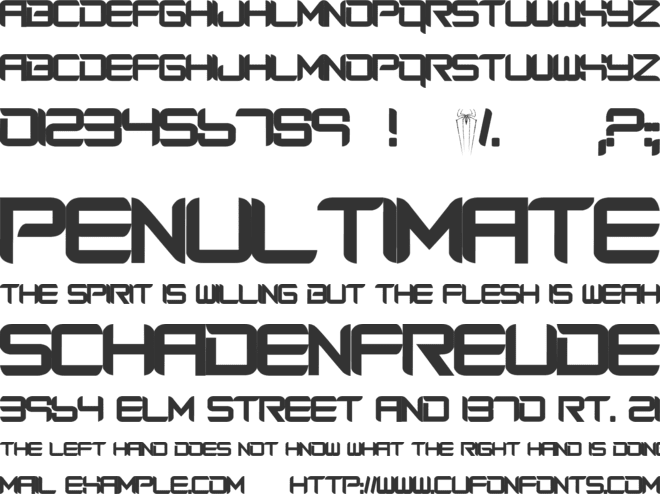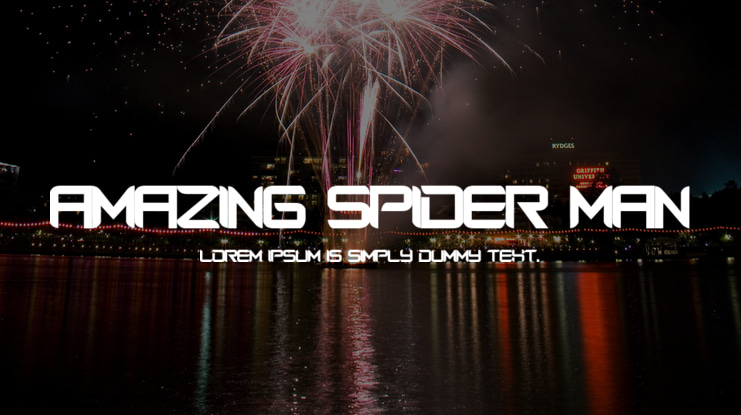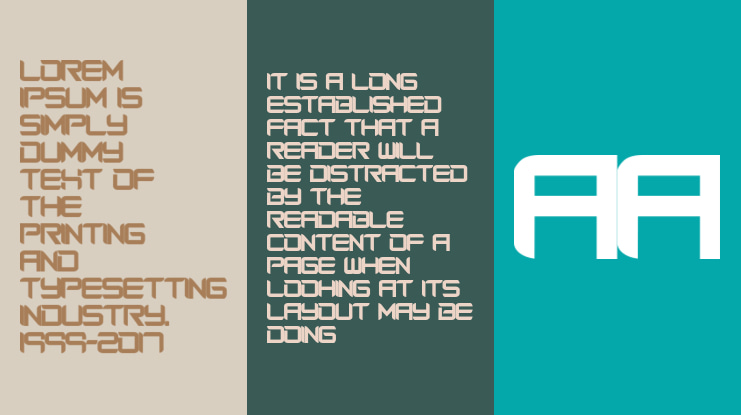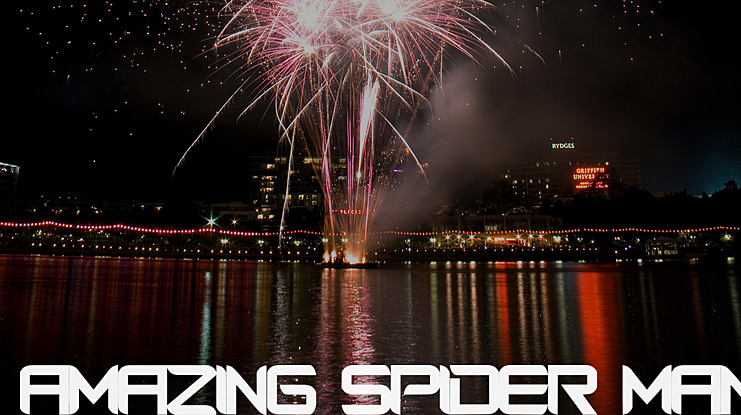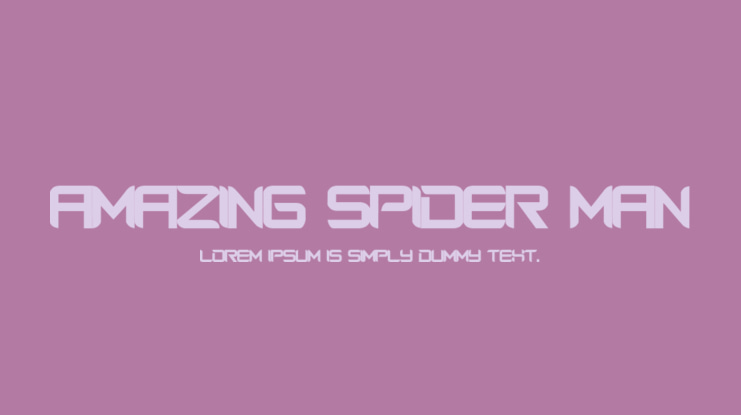
Amazing Spider Man Font Family
P. A. Vannucci
Direttamente dal film diretto da MARC WEBB e interpretato da ANDREW GARFIELD, il font inedito per tutti gli estimatori del film.
Directly from the film directed by MARC WEBB and starring ANDREW GARFIELD, the unpublished font for all admirers of the film.